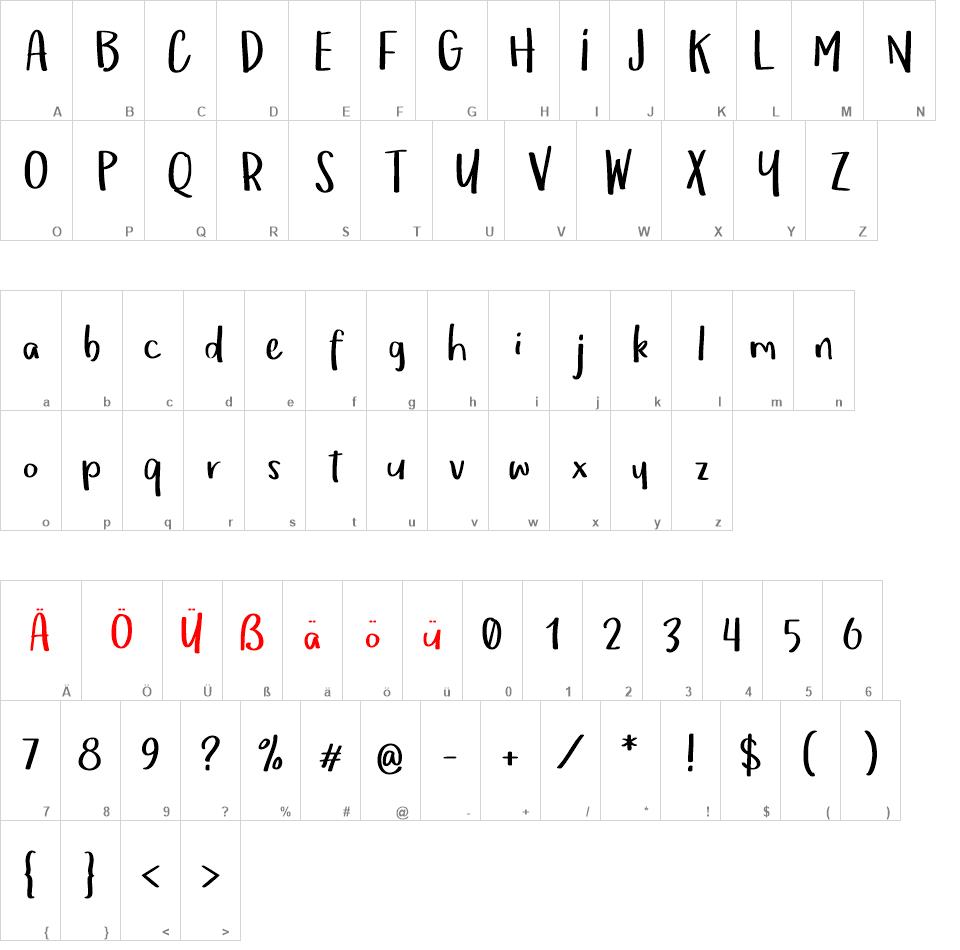
Om Telolet Om
Om Telolet Om font
Om Telolet Om
Diese Schrift nahm einen handschriftlichen Stil mit einer unregelmäßigen Form an. Wir wollen den Eindruck eines Natürlichen und Persönlichen vermitteln. Neben dem Grundcharakter bringt Om Telolet Om auch OpenType-Funktionen mit; stilistische Alternativen und einige grundlegende Ligaturen; So können Sie ein Design mit mehr Flexibilität erstellen.